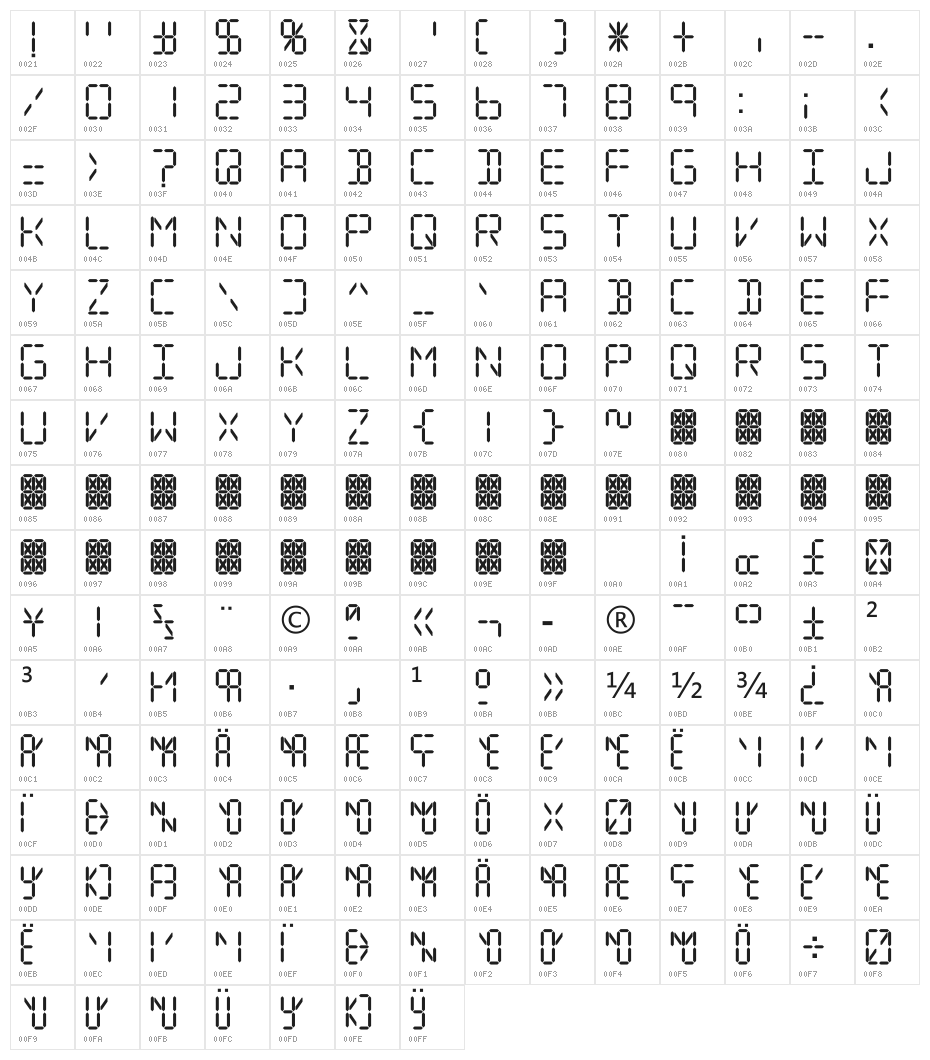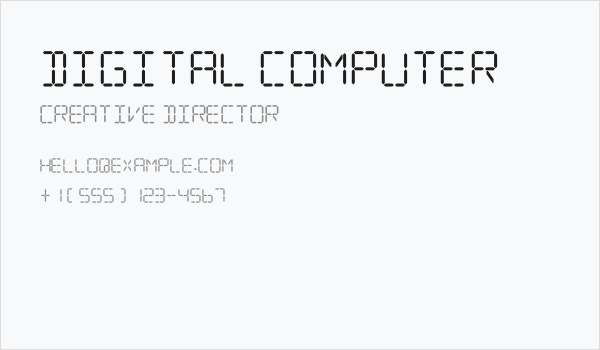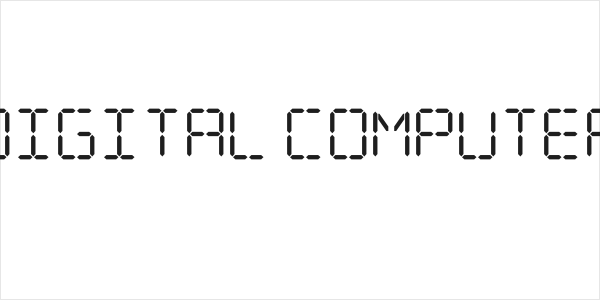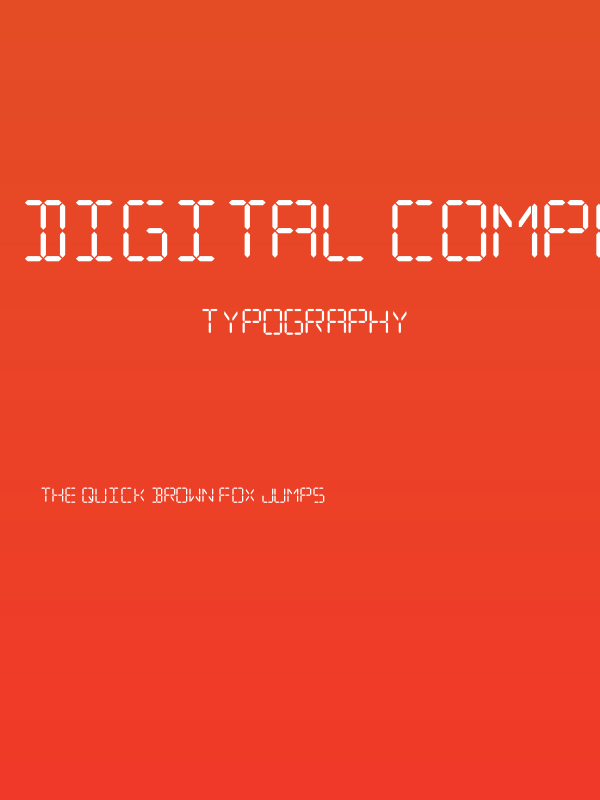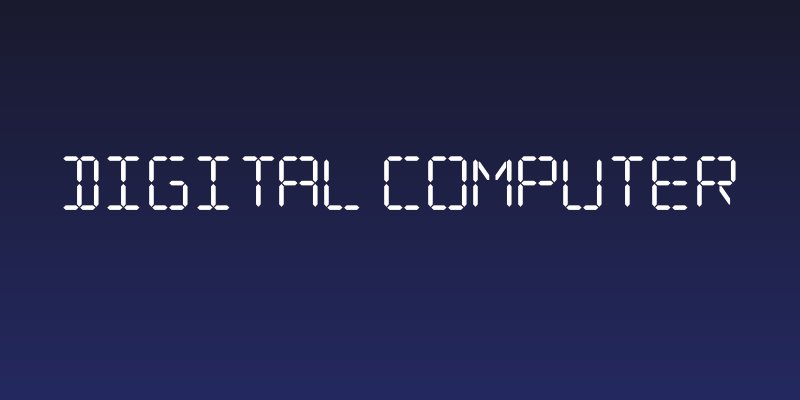
Digital Computer Font
| 整体风格 | Retro, Technological |
| 使用场景 | Headlines, Logos, Digital Displays |
| 推荐项目 | Suitable for digital-themed designs, retro technology projects, digital clocks, and tech-related branding. |